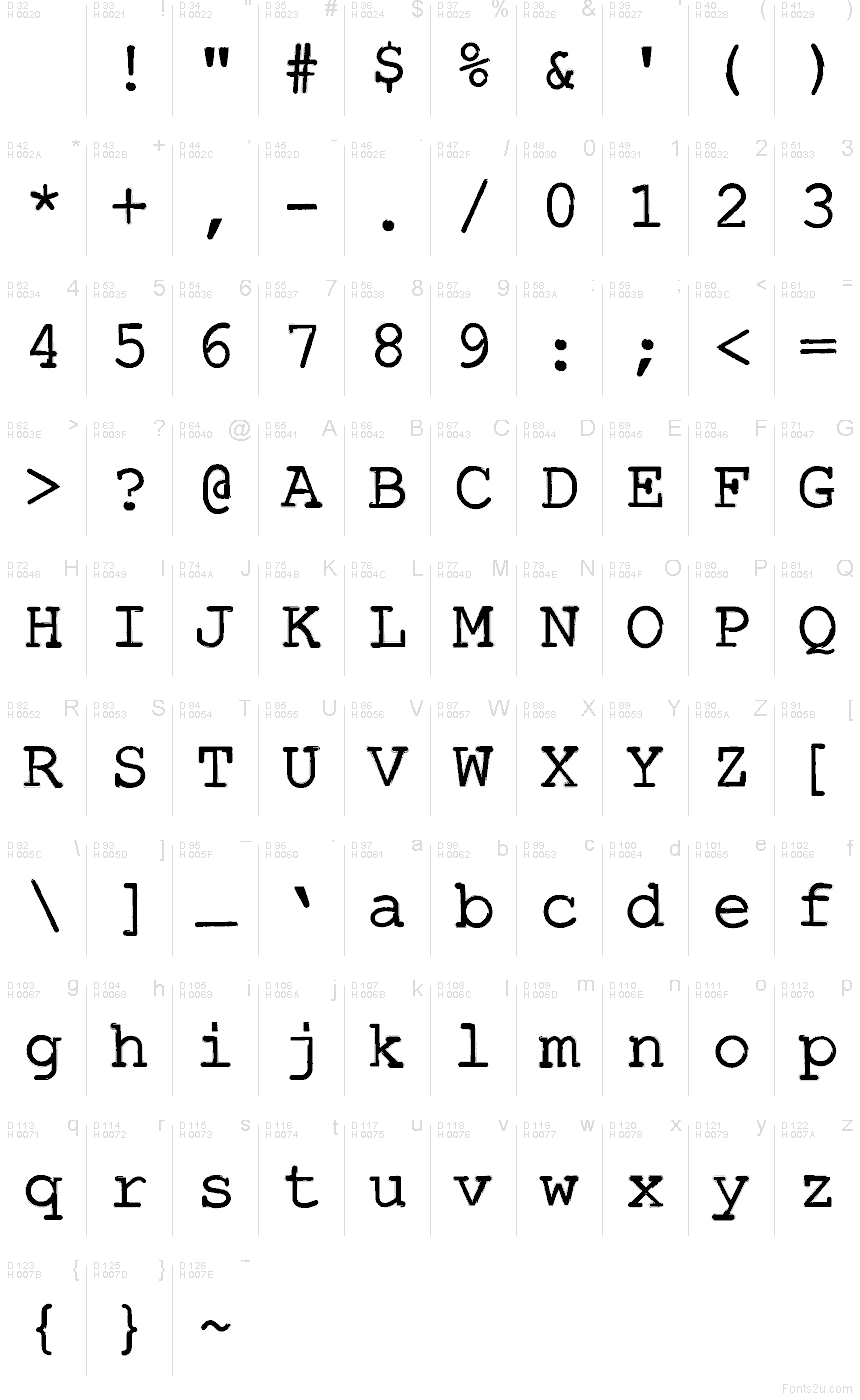
Typewriter Inked od Creativetacos je bezplatné, old schoolové display písmo inspirované vzhledem psacích strojů s lehce nedokonalými, inkoustovými okraji. Písmena využívají široké tvary typu slab, zaoblené rohy a texturu razítka, díky čemuž celý set působí dojmem skutečného potisku.
Typewriter Inked se skvěle hodí na titulky plakátů, vintage citáty, obálky knih, redakční prvky, štítky nebo retro branding, který potřebuje psací vzhled bez přílišného uhlazení. Tento bezplatný font sedne do layoutů, kde trocha textury pomáhá textu dodat ruční nádech, jako jsou obaly, kavárenské menu, ziny či papírnictví.